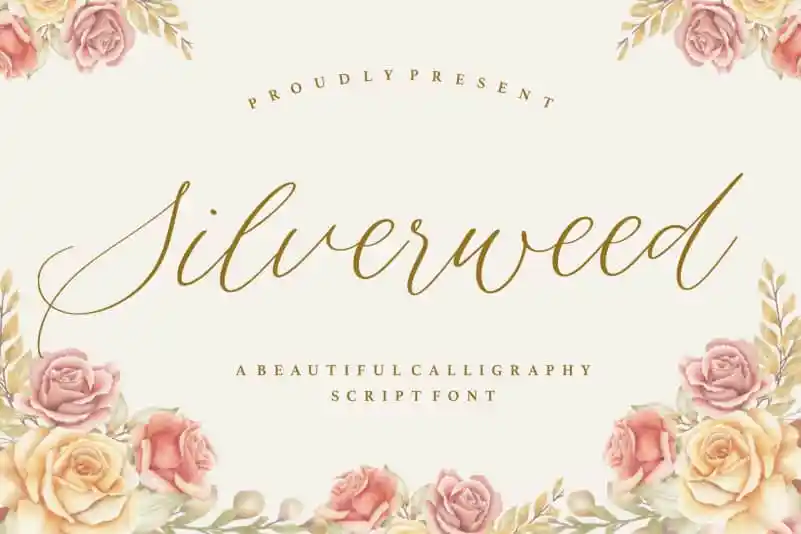
Silverweed Beautiful Calligraphy Script Font – Download Grátis
Silverweed Beautiful Calligraphy Script Font é uma excelente escolha para quem busca adicionar um toque especial às suas criações digitais com estilo elegante. Este script chama a atenção, combinando elegância com facilidade de uso, ideal tanto para trabalhos profissionais quanto para projetos pessoais. Criado pelo designer balpirick, o Silverweed oferece letras finas e detalhes sofisticados que ajudam a criar mensagens de texto impactantes e memoráveis. Seja em design gráfico, ilustração digital ou editoração de vídeo, este fonte adiciona um acabamento perfeito para sua produção. Não hesite em explorar e experimentar Silverweed Beautiful Calligraphy Script Font; certamente vai transformar a forma como você trabalha com texto!